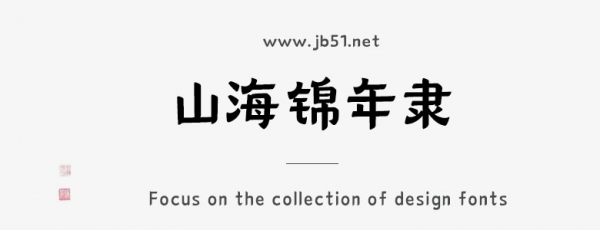
山海锦年隶家族
山海锦年隶家族是由山海字库出品的字体,这款字体笔触适中,字形端正,具有很好的视觉感,适合应用于艺术设计、平面宣传设计、网页设计,书法字帖等领域,需要的朋友可以前来本站下载。
字体介绍
山海锦年隶家族,由山海字体社出品。本字体为简繁字库,采用Adobe-GB1-5编码,包含常用简体(GB2312-80)6763个,繁体(GBK)2406个,共计9169个汉字;以及ASCII常用西文200+。6个字重一45-Light 55-Normal 65-Regular75-Medium 85-Bold95-Heavy